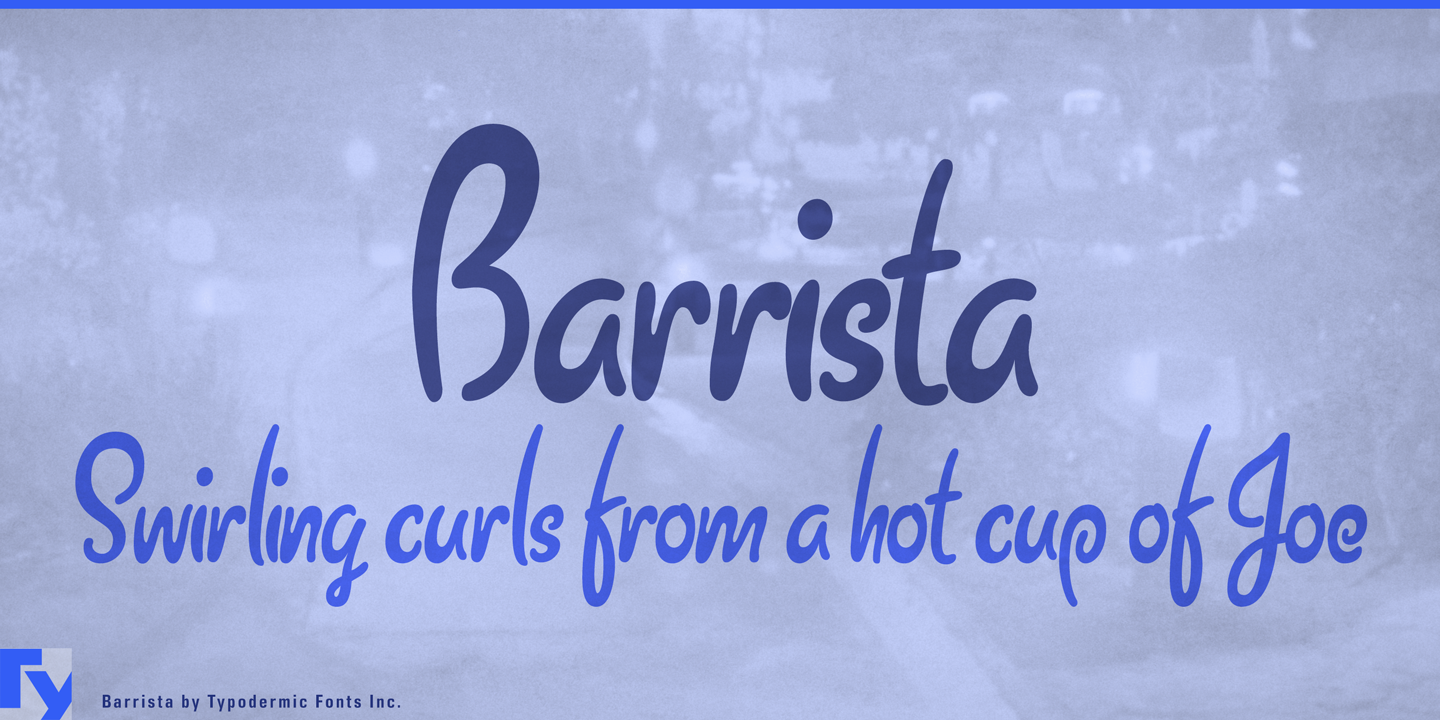
Barrista Font
A Barrista é uma fonte livre criada a partir de uma escrita à mão única, projetada para dar um toque elegante ao seu design. Esta fonte foi desenvolvida especificamente para uso como tipo de exibição e cabeçalho. Suas linhas curvas delicadas e detalhes únicos criam um visual autêntico que traz uma personalidade única a qualquer projeto. Ideal tanto para gráficos digitais quanto impressos, Barrista é perfeito para adicionar uma nota sofisticada à sua próxima criação. Desenvolvida pelo designer Hamilton, essa fonte oferece a oportunidade de incorporar um toque único e autêntico sem comprometer seu estilo, tornando-se uma escolha inteligente para quem busca agregar valor ao seu design com um grampo de personalização de alta qualidade.